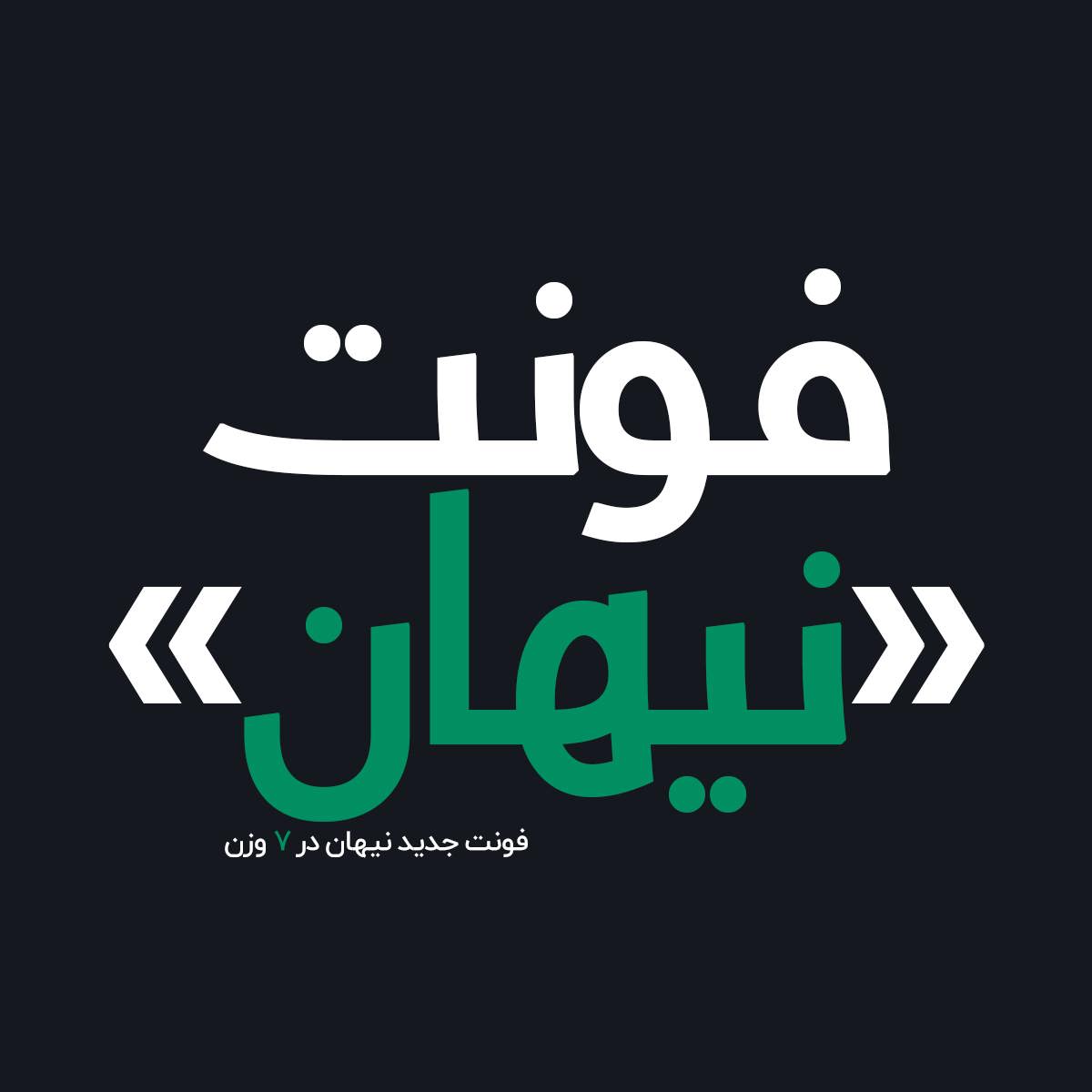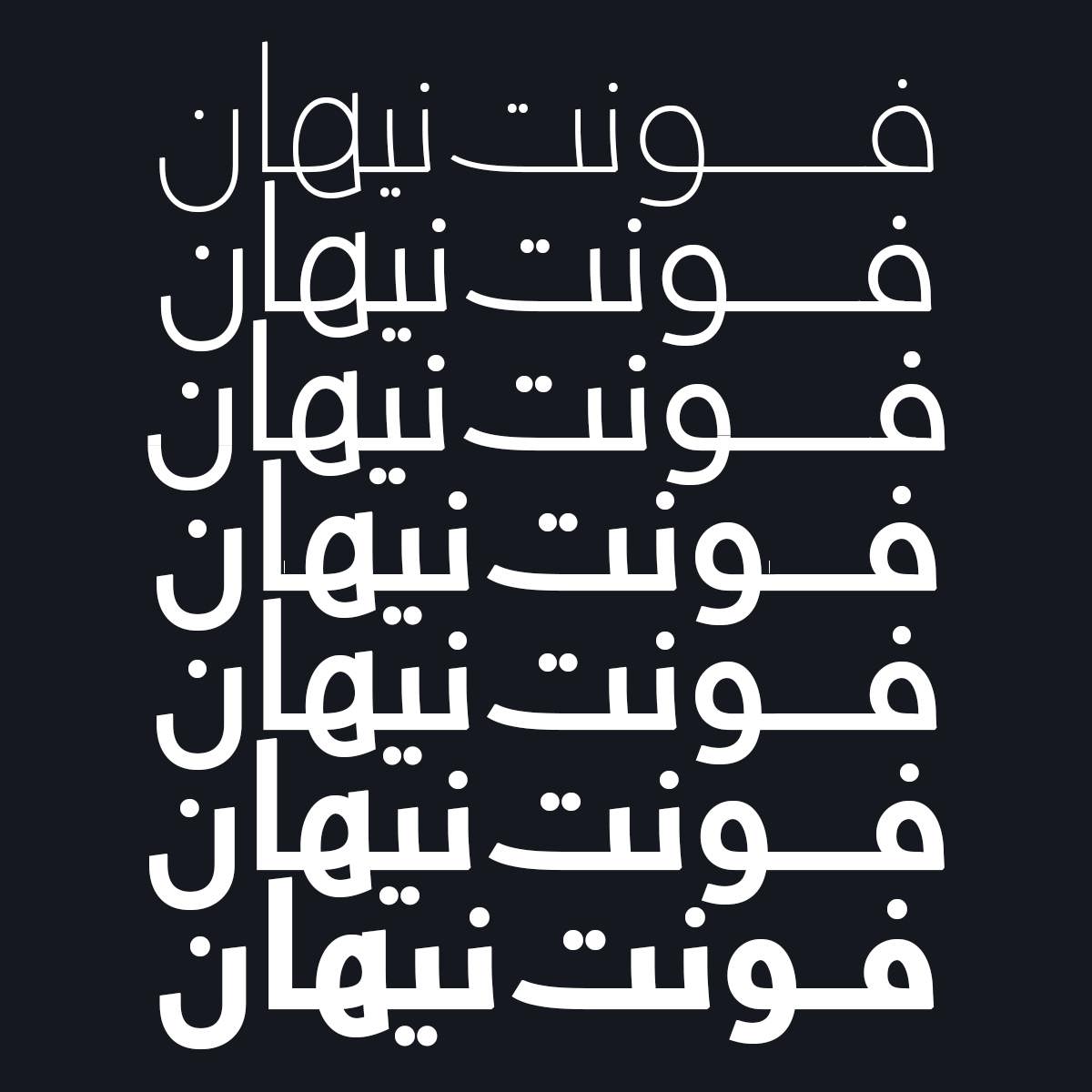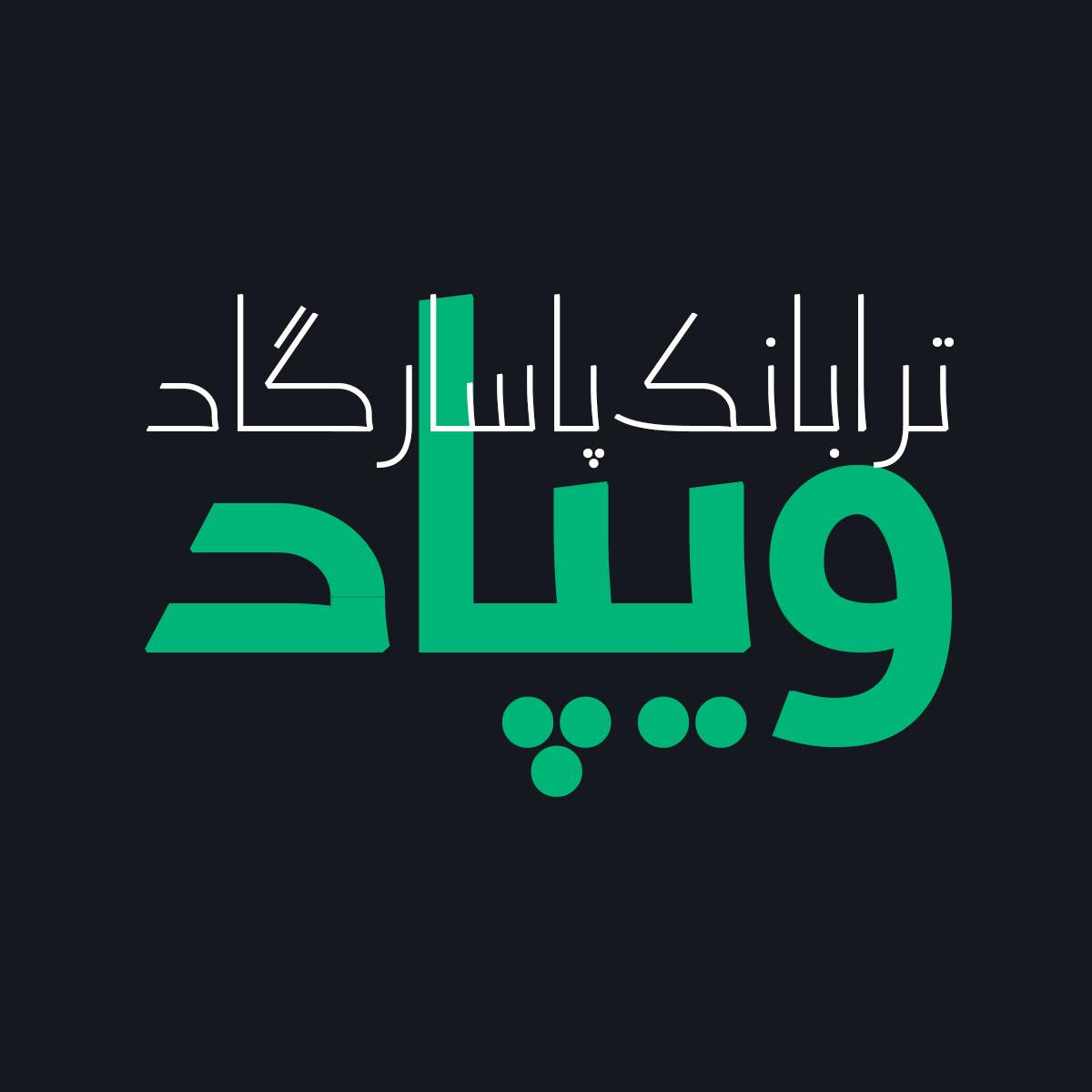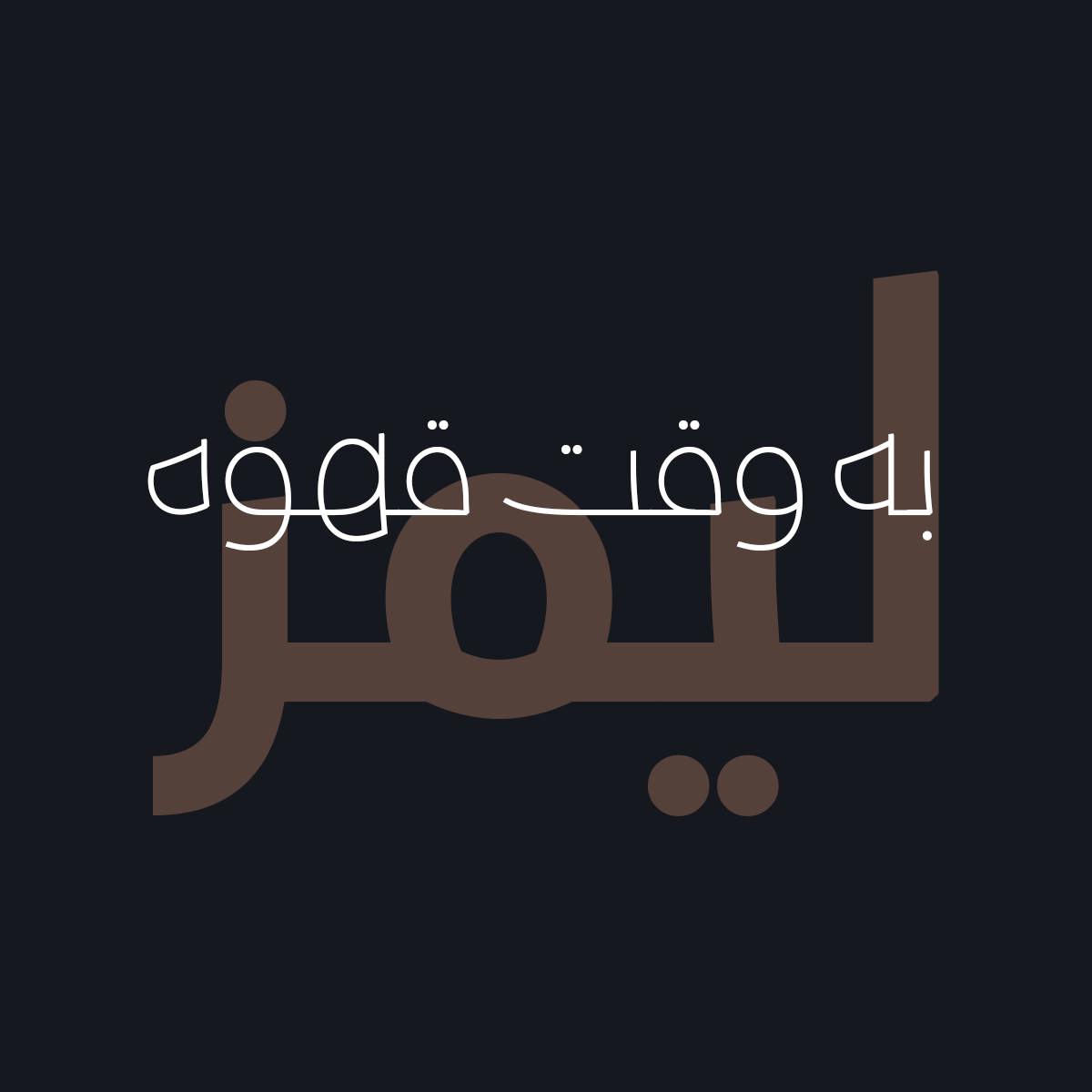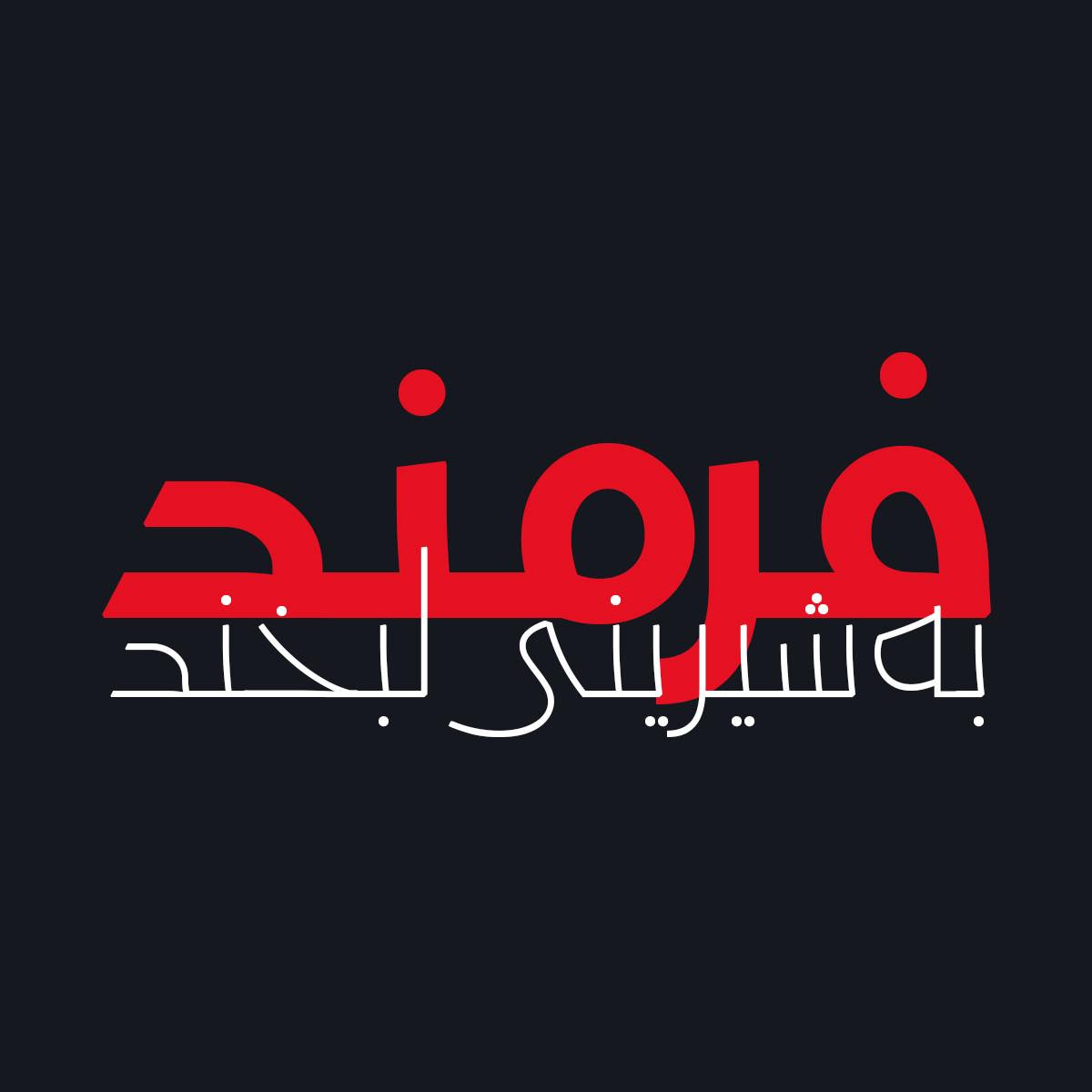
فونت فارسی نیهان Nihan Font
فونت فارسی نیهان یک فونت فارسی بر مبنای حروف هندسی و خاص می باشد که به طراحان گرافیک امکان خلق طرح های زیبا و حرفه ای…
فونت فارسی نیهان یک فونت فارسی بر مبنای حروف هندسی و خاص می باشد که به طراحان گرافیک امکان خلق طرح های زیبا و حرفه ای به سادگی یک تایپ میدهد.
فونت نیهان شامل 7 وزن و دارای منحنیهای بسیار گرد با پایانه های بسیار تیز است که این خانواده فونت را زیبا، دوستانه، مدرن و خوانا میکند. فونت نیهان با ارتفاع بالاتر از سایر فونتهای کلاس خود طراحی شده و برای متنهای طولانی، اندازههای کوچک و صفحه نمایش بهینه شده است تا خوانایی در ابعاد کوچک را در هر شرایط استفاده به ویژه برای فضای وب و صفحات دیجیتال واضحتر کند.
پیشنمایش و نمونه تایپ های فونت نیهان